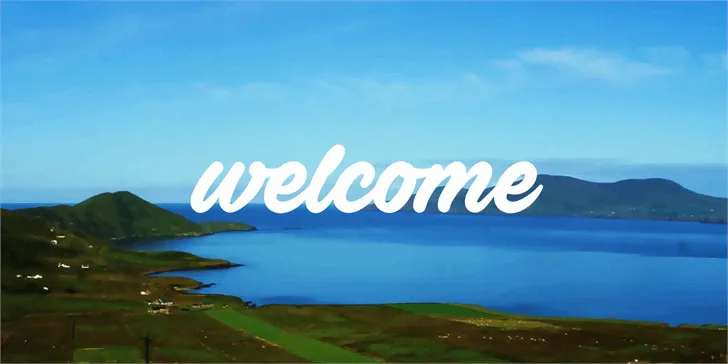
Ave Fedan é uma fonte escrita à mão criada pelo designer sueco Måns Grebäck em 2016. Seu estilo delicado e fluido é perfeito para aplicar um toque pessoal às suas criações digitais, seja em cartões de aniversário ou trabalhos artísticos. Este conjunto de caracteres elegante é ideal para aqueles que valorizam uma fonte escrita à mão moderna. Como parte da categoria de fontes escritas a mão, Ave Fedan oferece uma maneira fresca e original de adicionar personalidade às suas criações digitais. Para usuários finais, a fonte recebeu um tratamento cuidadoso que mantém sua essência enquanto lhe dá um ar pessoal. Ideal para os amantes da fotografia digital ou designers gráficos apaixonados por trabalhos artísticos e emotivos. Se você está buscando uma maneira única de incorporar em suas criações digitais, Ave Fedan é a fonte certa.